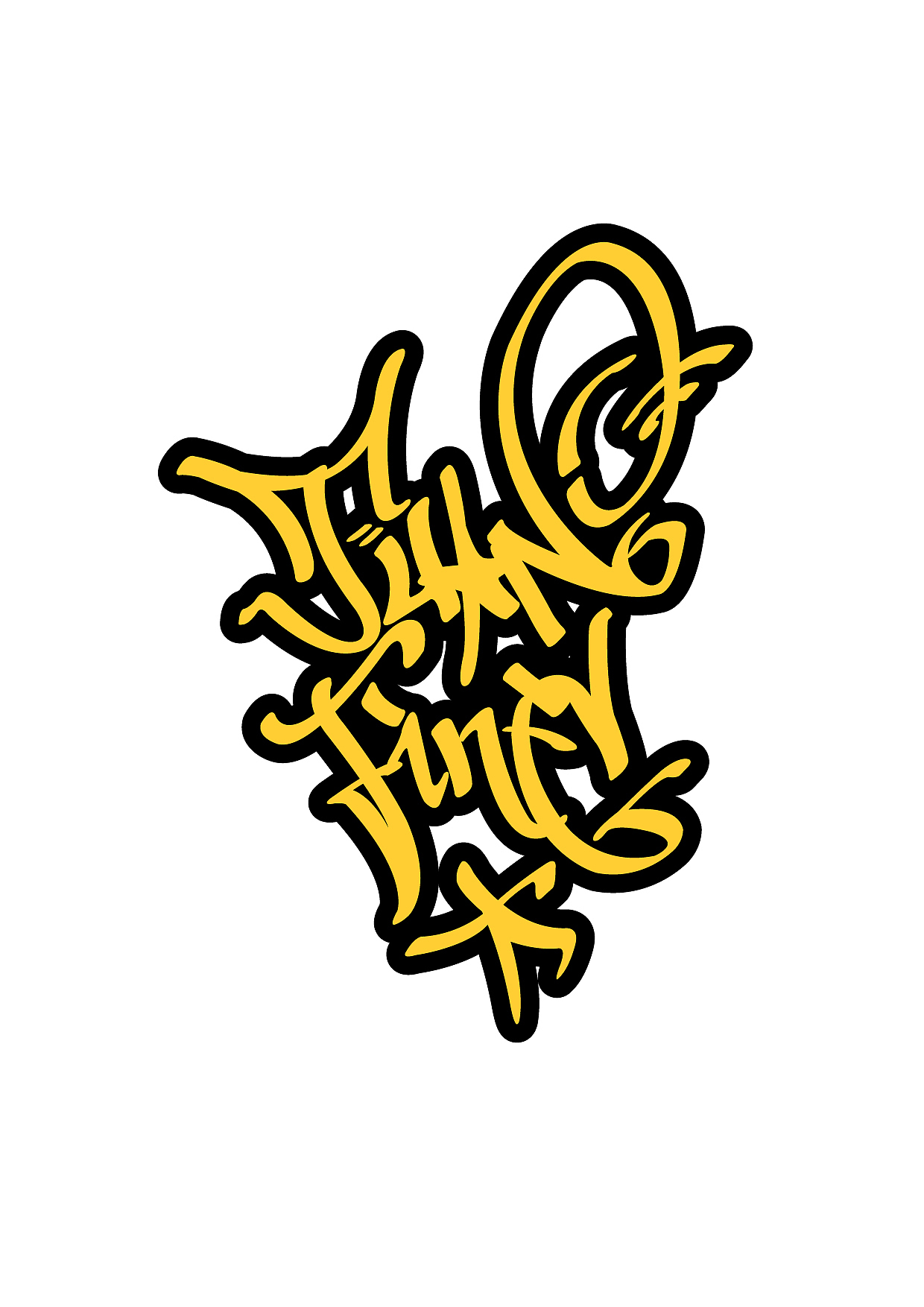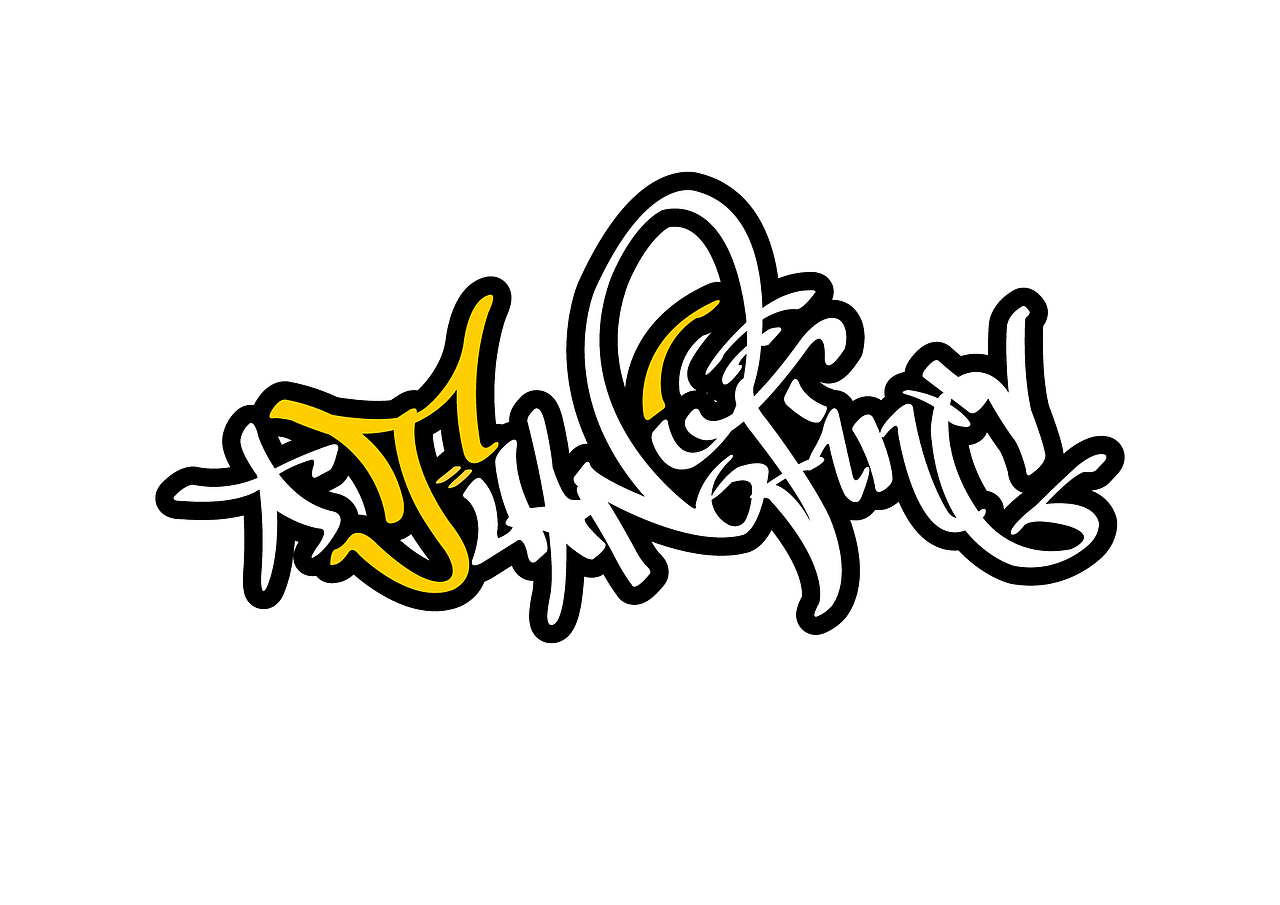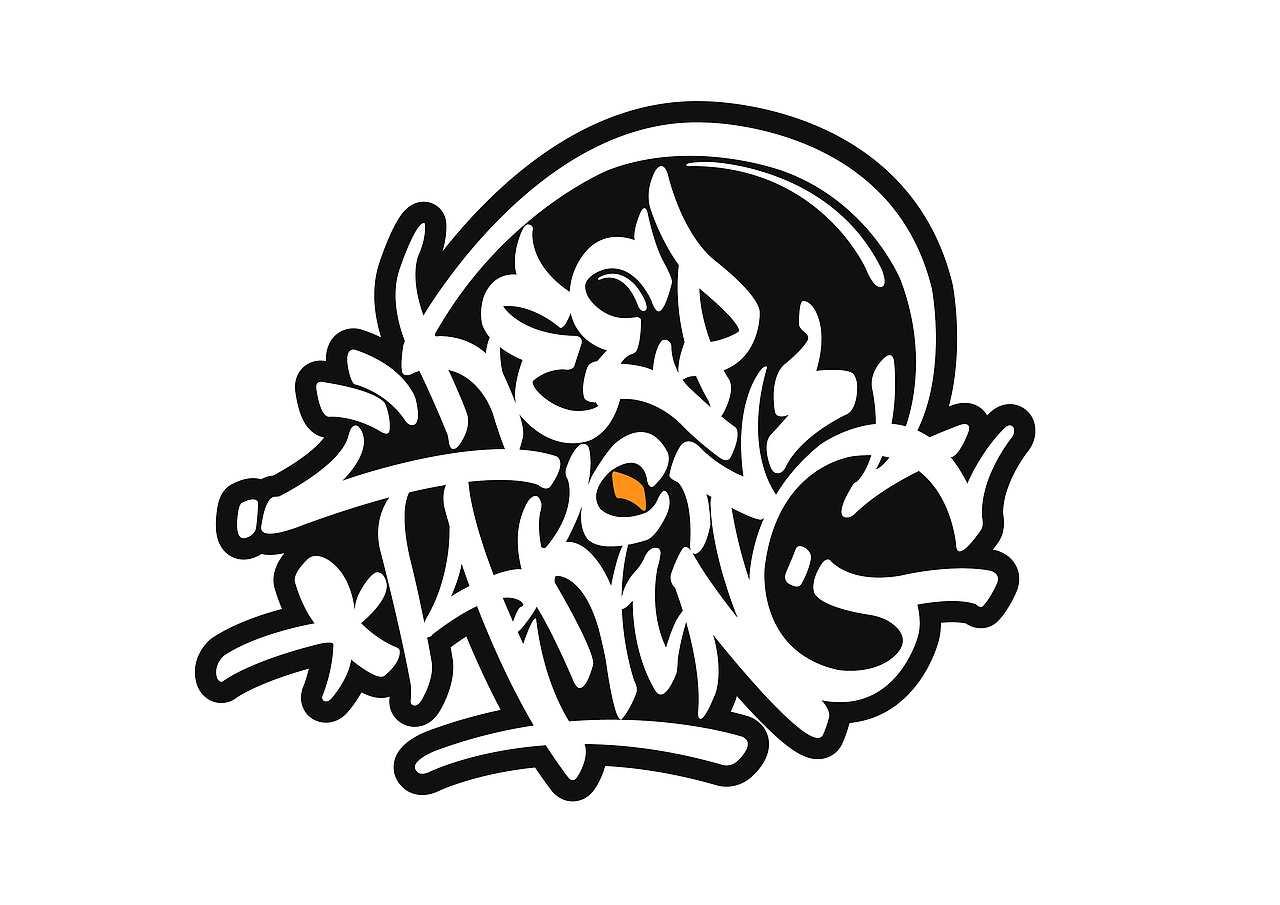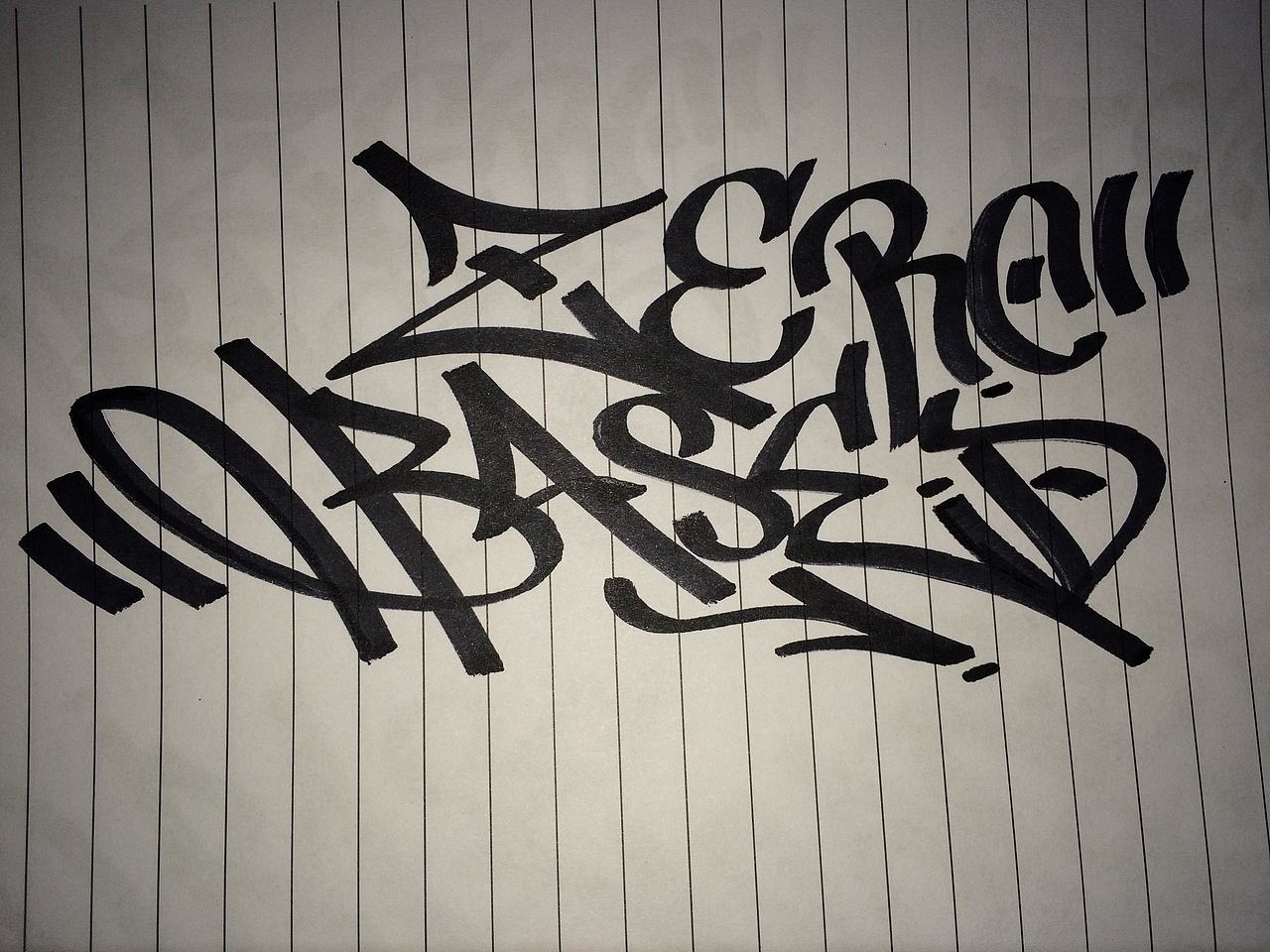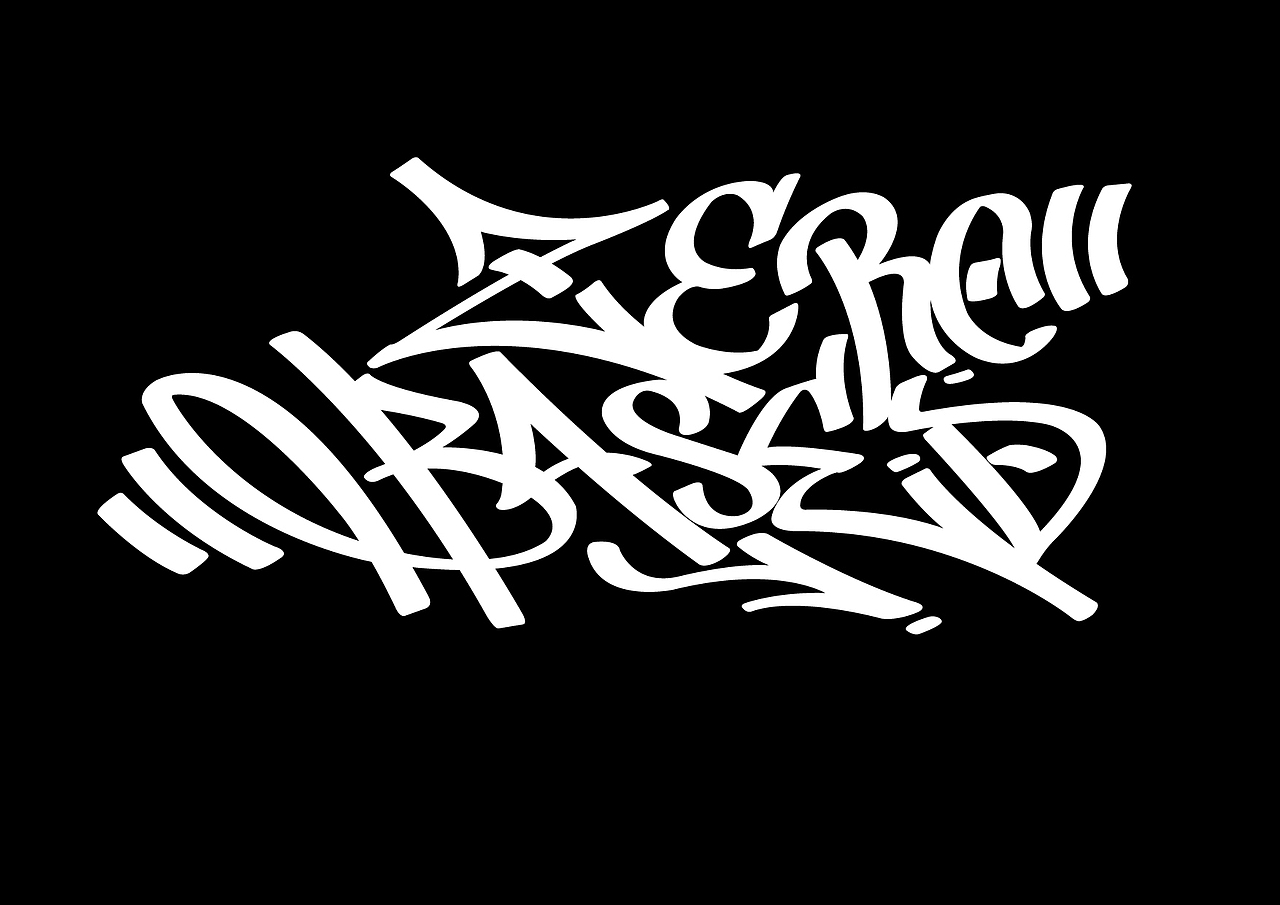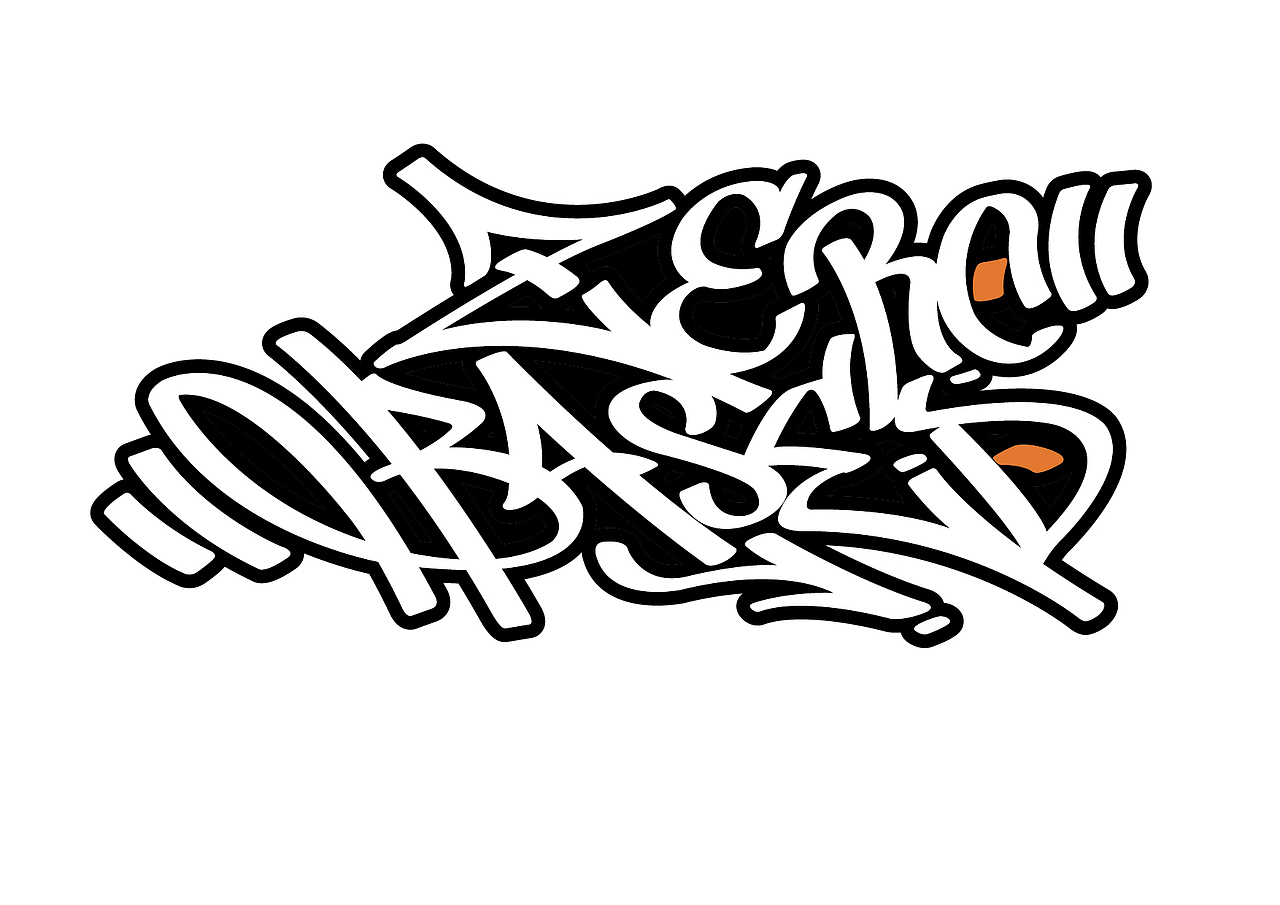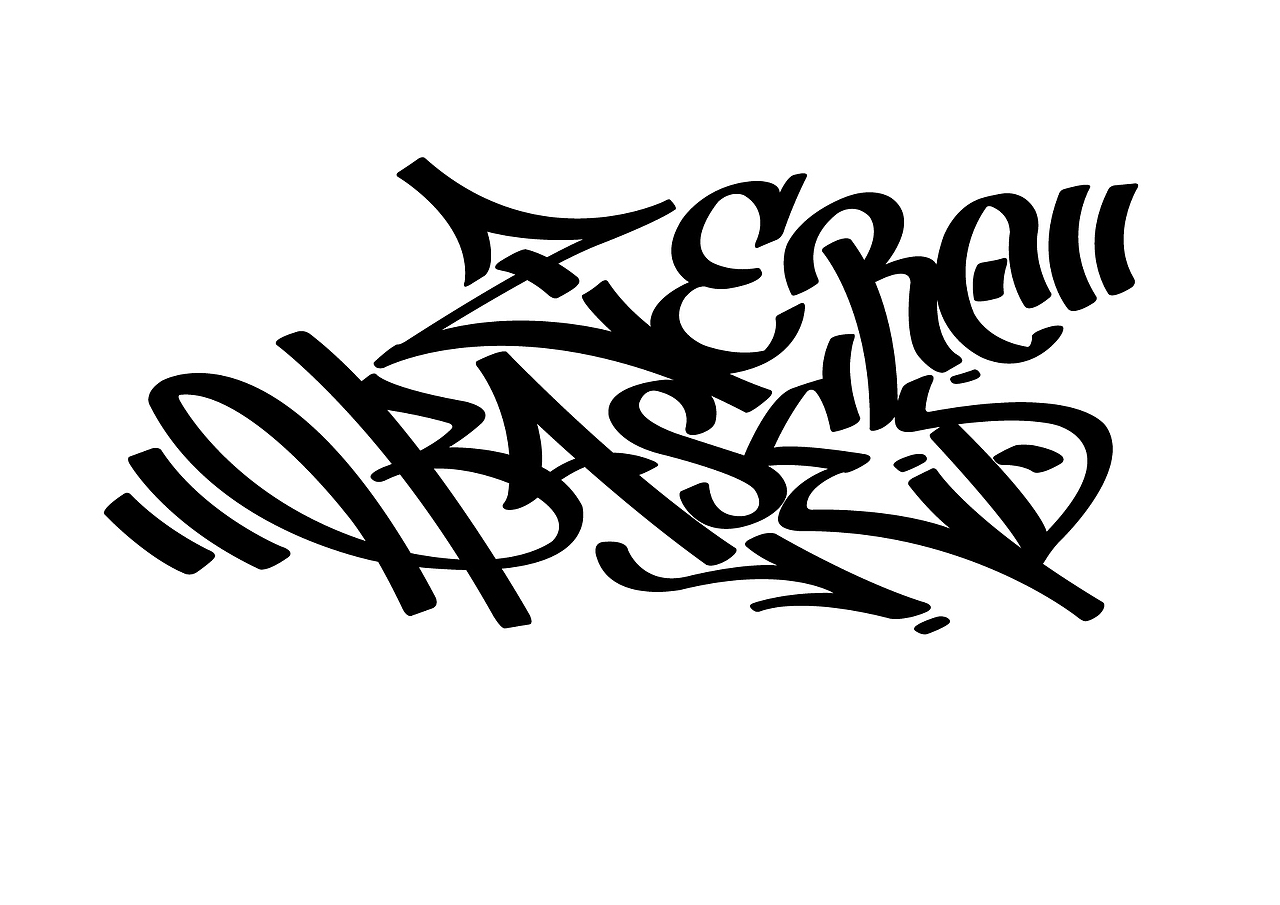
涂鸦TAG英文字体整理
都是先用铅笔写小小个的,试一下笔触啊怎么甩的,然后用大头马克笔写,通常一个TAG要写几十遍呢,再用AI抠,上颜色。感觉逐渐有进步了,加油。
YUAN JING
INTRO CREW 一个舞团的衣服图案 简称IC舞团
IC舞团
ZERO BASED.是零基础的意思
ETB'S THINK ETB全称ESSENTIALBALM 是我朋友的一个原创品牌 疯游精,TAG意思是疯游精的思想。
做任何事都必须KEEP ON TAKING,,坚持坚持。